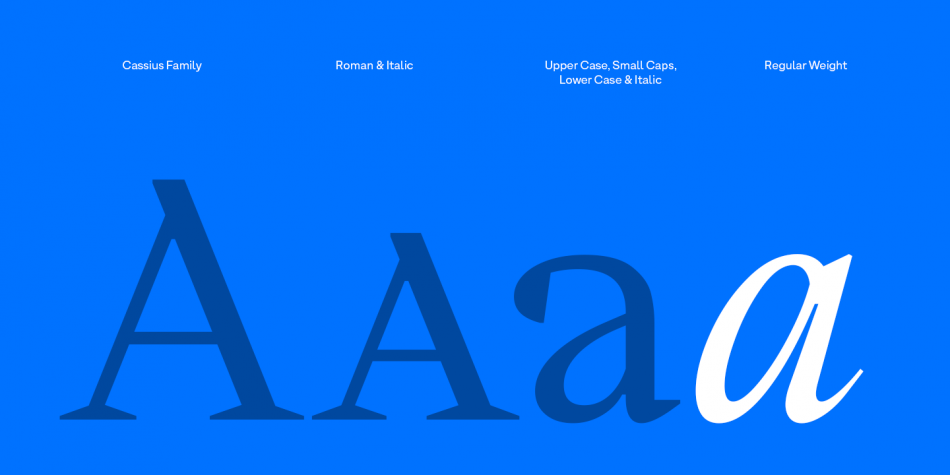
Was ist eine "Hipstergroteske"?
Der Begriff taucht in letzter Zeit hier ab und an mal auf - ich weiß nicht was das ist. Wäre nett, wenn das mal jemand erklären würde für ältere Mitbürger, die da nicht mehr auf der Höhe der Zeit sind ... Dankeschön!
Und ganz tief rein in den Klischee-Topf :-)
Hipster seien ja allgemein Menschen, die bestimmte Aspekte alter Szenekulturen (Populärkultur, Handwerk, Sport, ...) in ihre eigene Lebensweise und Selbstdarstellung aufnehmen, pflegen, überhöhen, ... – manchmal ganz konsequent, manchmal selbstironisch, manchmal unreflektiert und konsumistisch. Als Beispiel seien die Bärte (Barbar-Kultur), Bierbrauen (Craftbier), Radfahren (Fixies oder Waffenräder), Gaming (80er-Retro), Musikwiedegabe (Vinyl ab 180g halfspeed-cut), ... ... genannt. Also irgendwie "die guten Aspekte der alten Dinge" in neuen Kontext gestellt, entweder wirklich oder als Manierismus oder Zitat oder ...
Angewendet auf Schrift tauchen dann oft Remakes der ersten Grotesk-Schriften auf, ein bisschen Jugendstil, ein bisschen Moderne, ein bisschen Plakatschrift-Proportionen, ein bisschen Handmade-Dreck, ... (weiters manchmal Fotosatz-Optik, oder 90er-Digitalismus, oder Zeitungs-Antiquas, oder klassizistische Display-Schriften) die dann für Darstellung von z.B. oben genannten Themen in Kontext gesetzt werden.
Als Schubladisierung sind dann neue Schriftarten, die bewusst ein wenig "alt" aussehen oder ein bisschen seltsam oder ein bisschen zu auffällig, als Hipsterschriften eingeordnet – ich würde sagen da geht es eher um die offensichtliche Einsatzfähigkeit für solche Zwecke, als um eine ganz bestimmte Form.
Hipster-Designmoden lassen sich meiner Meinung am Besten bei Websites wie creativemarket, creativefabrica oder, wenn man mehr Zeit hat, bei Pinterest beobachten. Hipster wollen hipper als hip sein und uniformieren sich in diesem Anspruch quasi. Daher diese Schwemme an handwritten fonts, die alle totaaaaaaaal hip und individuell sind. Und zumeist potthässlich (meine Wertung, andere haben andere Meinungen).
Zur Zeit ist es ja total cool, Logos bis zur Beliebigkeit zu simplifizieren. Daher wäre mittlerweile auch Helvetica und Konsorten für mich zur Zeit eine Hipster-Schrift.
Auch diese Unmöglichkeit, heute noch eine einfache Tasse Kaffee zu bekommen mit einem angemessenen Preis-Leistungsverhältnis, ist Ausdruck der Hipster-Menschen, die, Apple-Macbooks nutzend die Starbucks, Coffee Campus, ... dieser Welt zu ihren Büros auserkoren, dort mit Over-Ear-Kopfhörern sitzen, auf denen dann stolz Marshall steht oder die Beats in die Welt trugen, die einfach nur matschig klingen, aber eine zeitlang hip ohne Ende waren, bis der Mainstream der Apple-Jünger und Wannabees die auch kauften.
Männliche Menschen, deren Frisuren, Bärte und Kleidung den Eindruck vermitteln, als kämen sie direkt aus einem kanadischen Baumfällercamp, sich aber dann über die Vorteile von Q10 im Vergleich zu Hyaloronan in ihrer Tagesgesichtscreme unterhalten und nicht mal einen Nagel in die Wand hämmern können, jedoch eine Werkzeugausstattung besitzen, die gestandene Handwerkern die Tränen in die Augen treiben. Menschen, die nicht zum Döner- oder Sushimenschen ums Eck gehen können, sondern sich einen Foodtruck vor die Tür bestellen.
Und falls ich den Eindruck erweckt haben sollte, ich mag diese Kultur nicht, dann ja, das stimmt: Wenn Du willst, dass etwas aussieht wie handgemacht, dann mach es mit der Hand! Deine Existenz wird für Dich nicht besser, wenn Du dein Yuppie-Dasein mit einer Tünche fremder Subkultur tarnst. Damit wirst Du nur zum Bobo. Und verhasst bei all denen, deren Ausdrucksmittel Du Dir in Deiner eigenen Orientierungslosigkeit aneignest. Du bist nicht Grunge, Du bist nicht Holzfäller*in, Du bist nicht Naturbursche/-mädel, Du bist nicht audiophil, Du bist nicht nachhaltig, Du bist nicht individuell, Du bist nur eine Kapitalismusdrohne wie alle anderen auch.
Ich greife jetzt einfach mal diese Passage heraus und widerspreche dir hier.
Der Zustand den du beschreibst trifft höchsten auf die Zentren von Großstädten zu. Bereits in den Randgebieten der selben wird es schon schwierig etwas anderes als über Stunden warmgehaltenen Filterkaffee niedrigster Qualität zu bekommen.
Die Kaffeeszene ist beispielsweise extrem nerdig/kreativ und ich würde das nicht sofort ins Negative ziehen. Das was nervt ist wenn der Mainstream sich auf diese Bereiche stürzt (weil sie Profit versprechen) und man plötzlich bei Netto Pseudo-Craftbier bekommt. Die eigentliche Craftbier-Szene macht genau das was du forderst — sie brauen ihr Bier selbst, zuhause oder schon professioneller und oft mit ziemlicher Hingabe (ich kenne da zufällig einige).
Ich verwende den Begriff oft ironisch und meine damit eher einen etwas übertriebenen Zeitgeist. Der kann amüsant sein aber natürlich auch nerven — wie die meisten Dinge.
Stört ist vielleicht das falsche Wort – es fällt aber sicher auf und das soll es bei den Hipster-Fonts ja auch. Schrullige Details gehören ja zum Konzept …
Gibts eigentlich einen Namen für diese Form von M, N, Z und A (Siehe Neue Power)?
Ein offizieller Name dafür ist mir nicht bekannt. In einschlägigen Kreisen war für diese Formen vor ein paar Jahren mal die Bezeichnung »brutalistisch« (“brutalist”) geläufig. Der Gedanke ist zwar nachvollziehbar; vielleicht wollte man aber auch nur auf dem Trittbrett des entsprechenden Trends mitfahren.